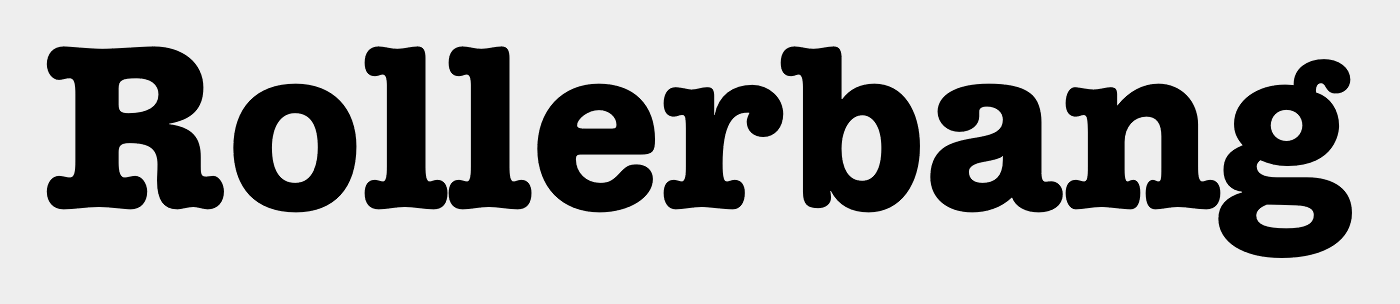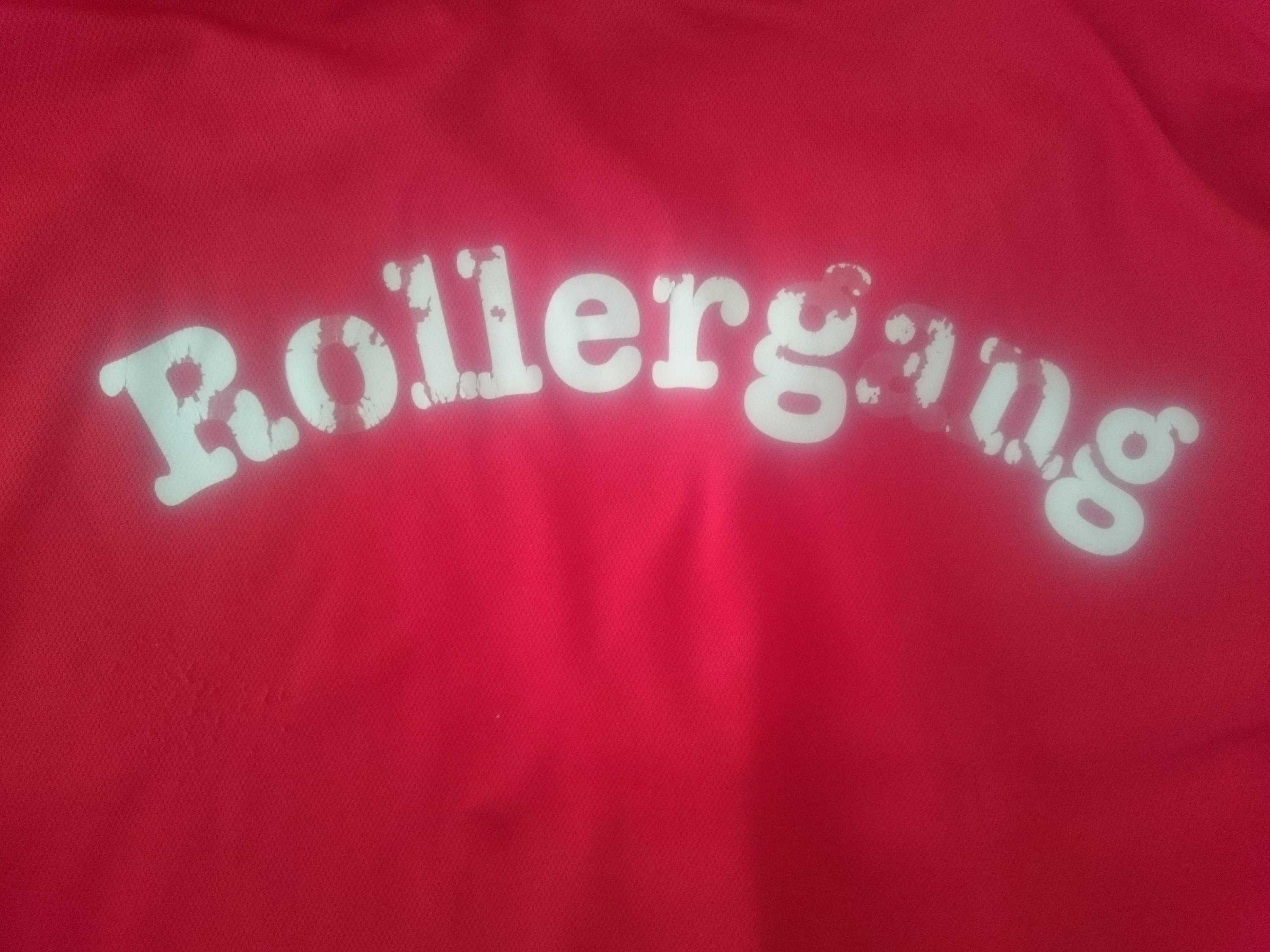
Suche Schriftart von "Rollergang"
kennt jemand die Schrift von Rollergang?
Bei dafont.com unter dem Menüpunkt "Serifen" bin ich leider nicht fündig geworden.
Die Schrift wurde an einer ovalen Form ausgerichtet und ist im Original natürlich nicht so...